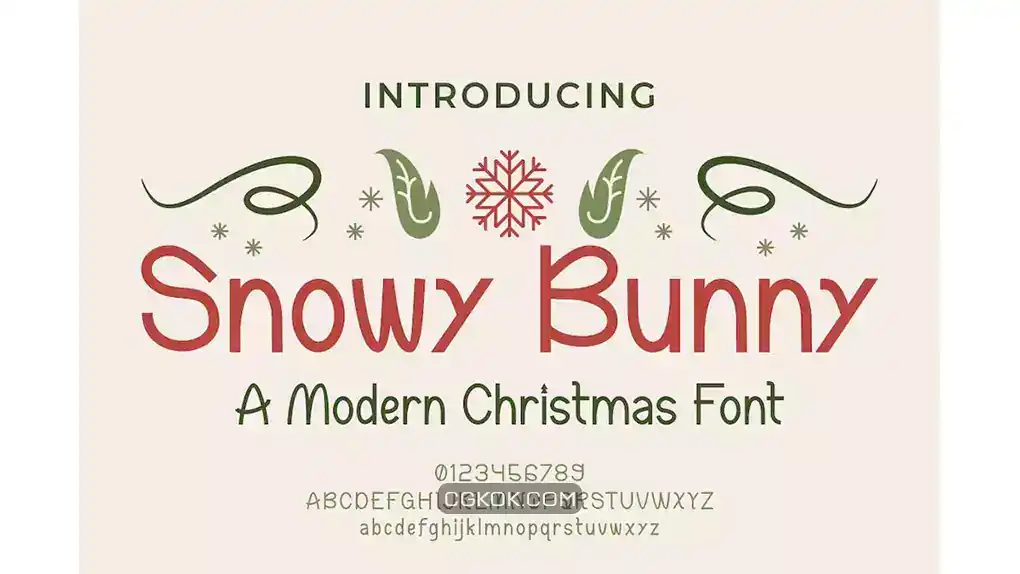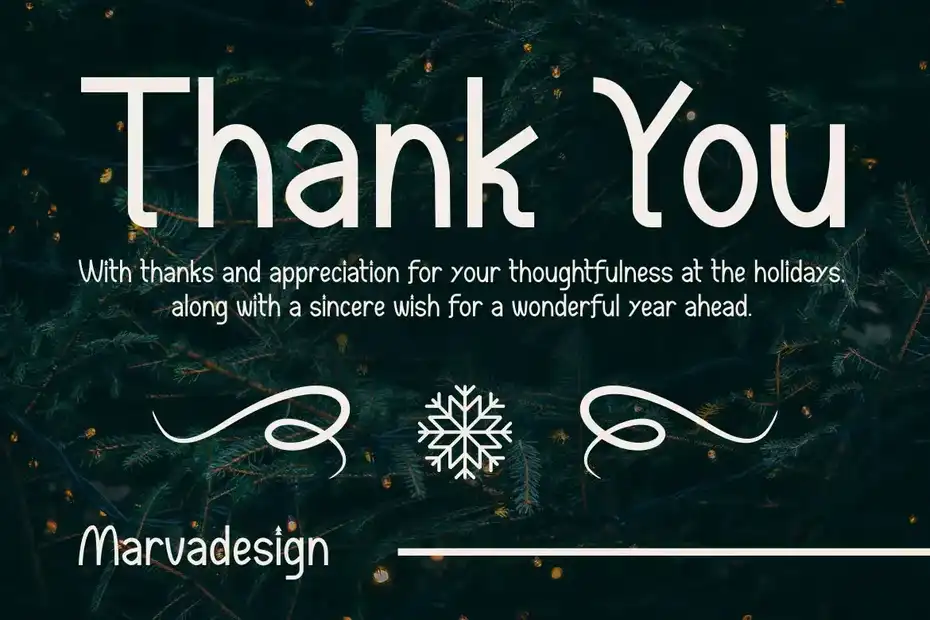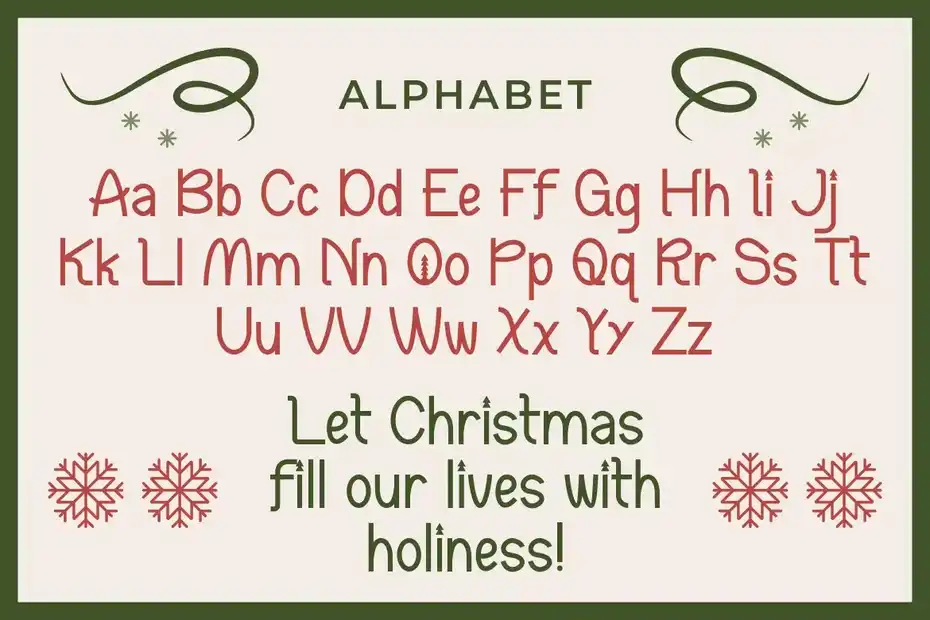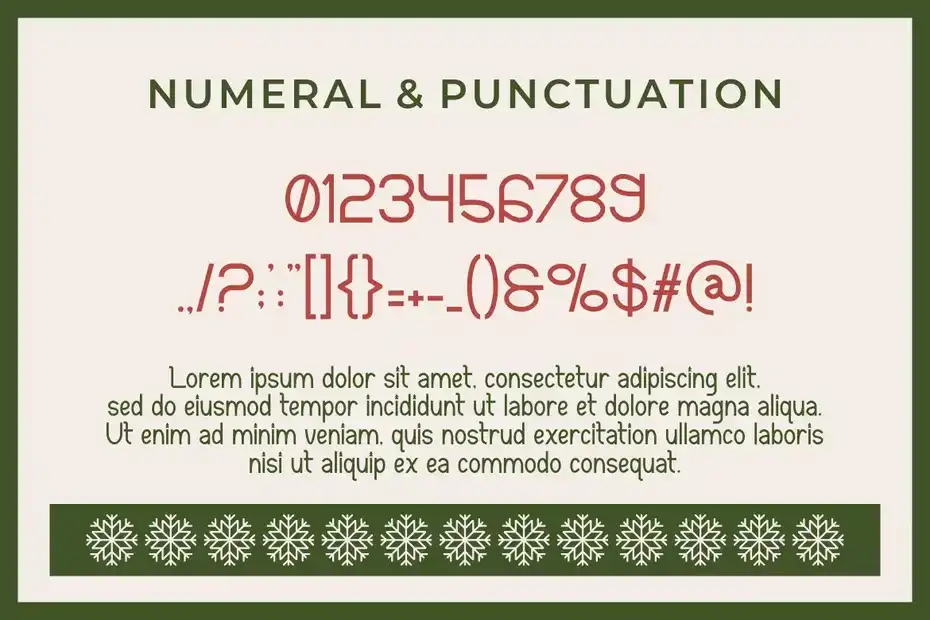
دانلود فونت انگلیسی مدرن کریسمس Snowy Bunny – A Modern Christmas Font
فونت انگلیسی مدرن کریسمس : این فونت یک فونت نمایشگر برجسته و معتبر است که برای پروژه های برندسازی مانند: لوگو، چاپ تیشرت، محصول و غیره مناسب میباشد.